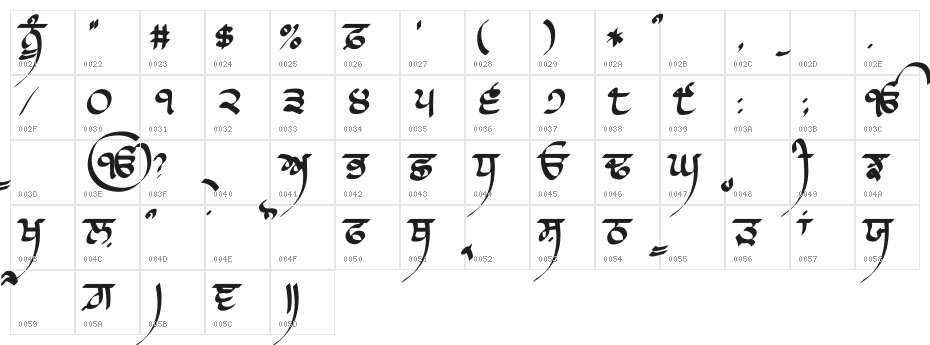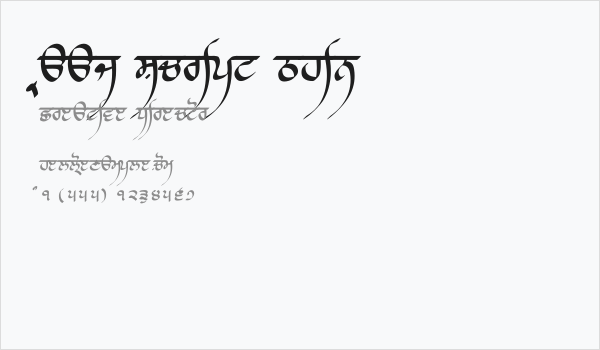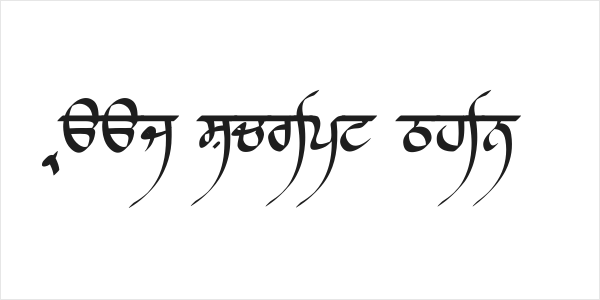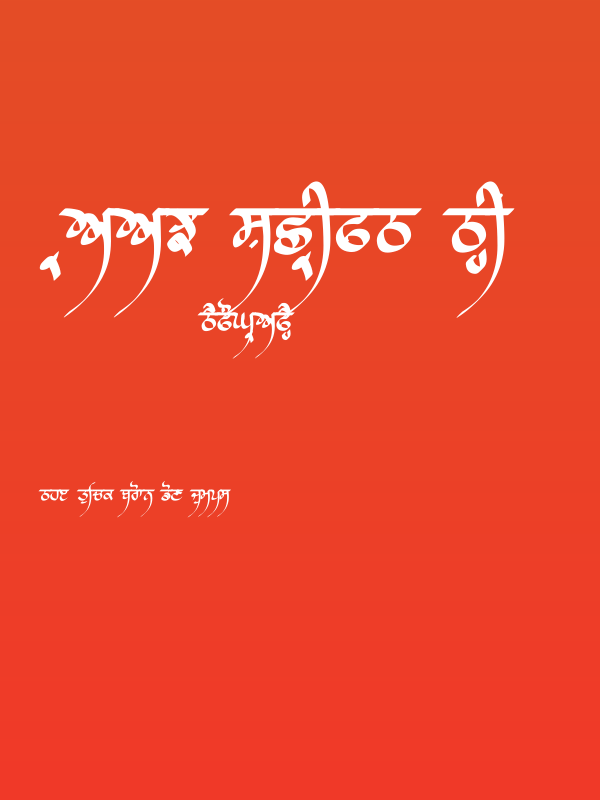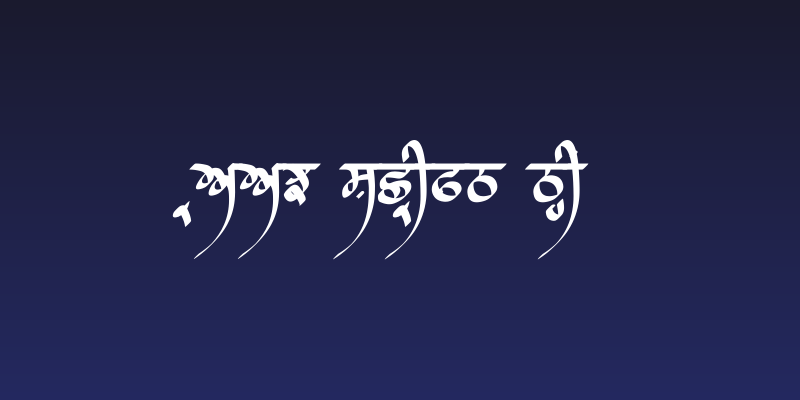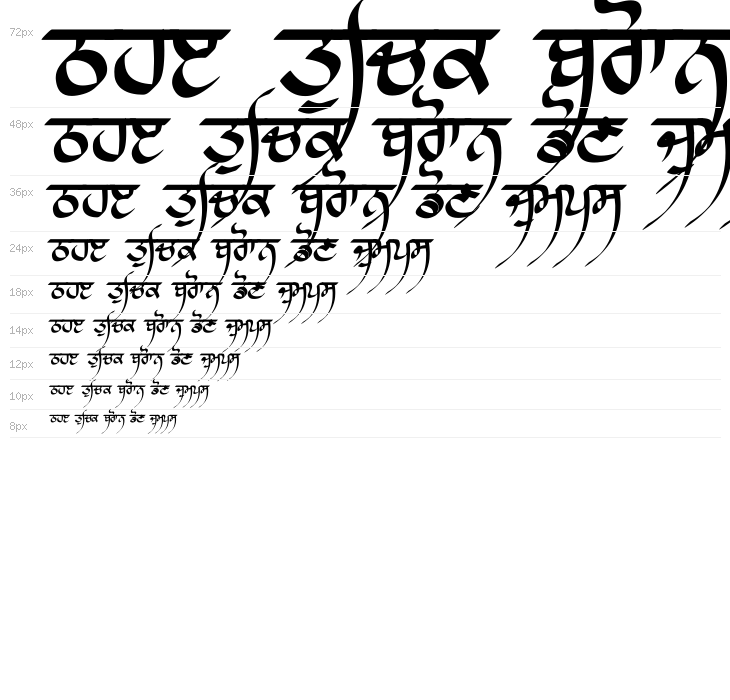
Raaj Script Thin Font
| Stile generale | Elegant |
| Caso d'uso | Logos, Invitations, Artistic projects |
| Progetti proposti | Ideal for wedding invitations, elegant branding, artistic posters, and sophisticated stationery. |